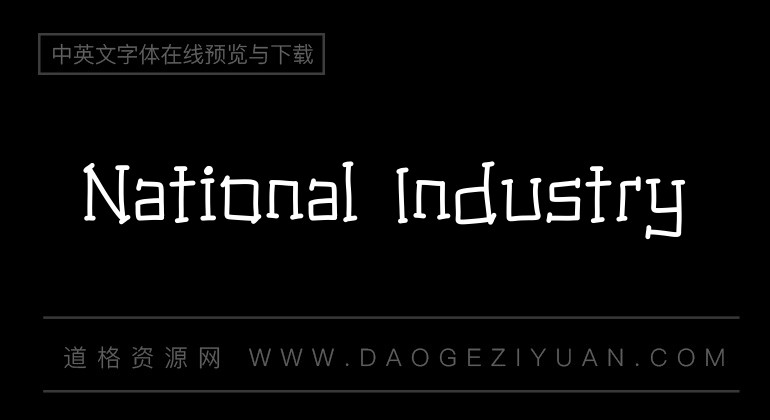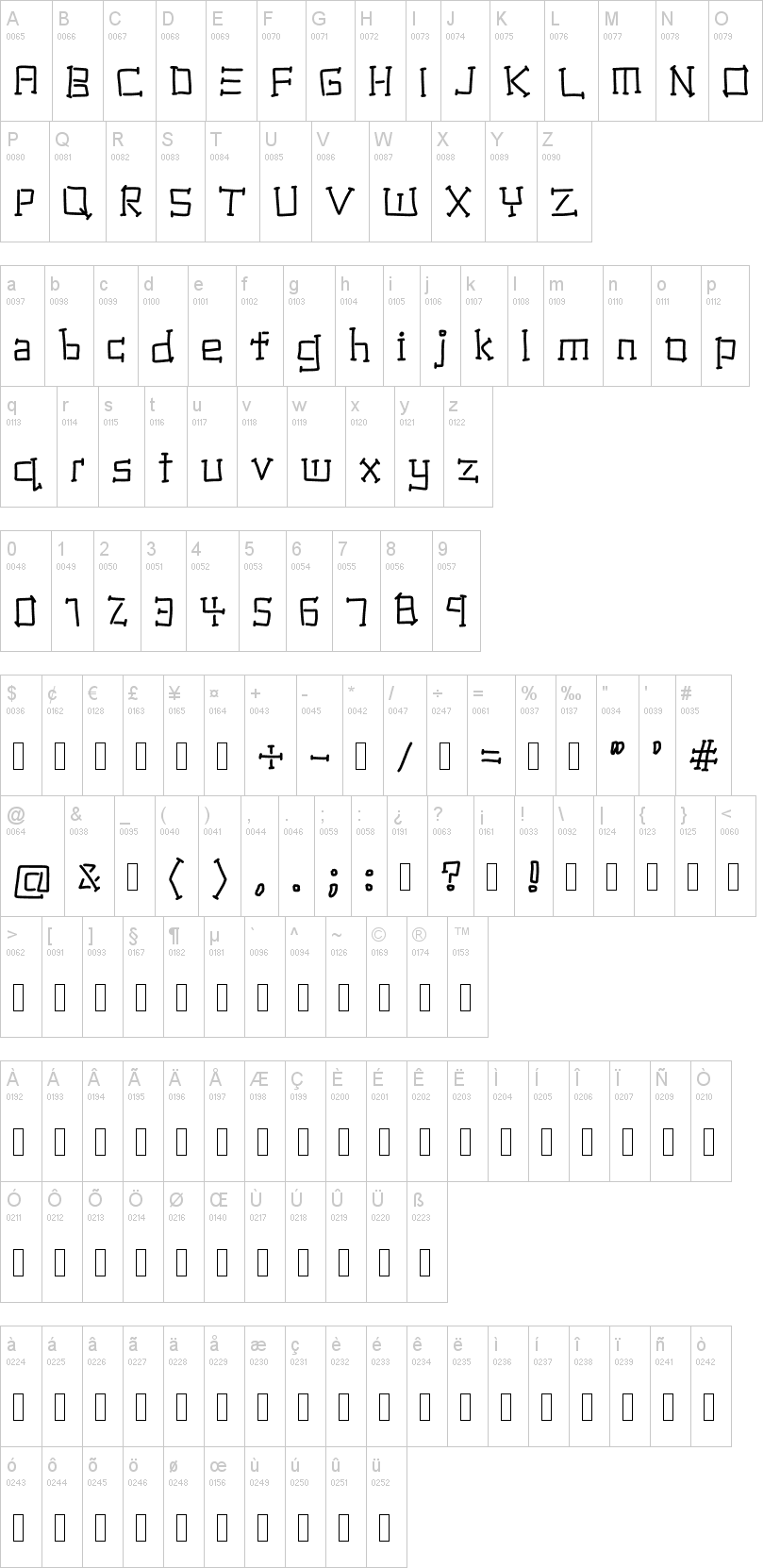
National Industry
? National Industry 字体是一种经典的工业风格字体,由美国设计师 Roger Roberson 于1937年设计。这种字体具有细节丰富的线条,粗犷的字母形状,极具特色的英文字母,以及一种简约而优雅的风格。它的独特外观和极具表现力的表现,使它成为许多设计师和印刷商的最爱。National Industry 字体可以用于标志、海报、海报、广告、包装、电视、电影、书籍等设计项目,为设计师提供了一种有趣而充满活力的字体。
National Industry是一款非常不错的手写艺术字体,具有很好的视觉感,适合于文化类的宣传设计、商业类品牌的广告和产品包装设计以及个性化文字排版等较多场景。
National Industry字符映射图